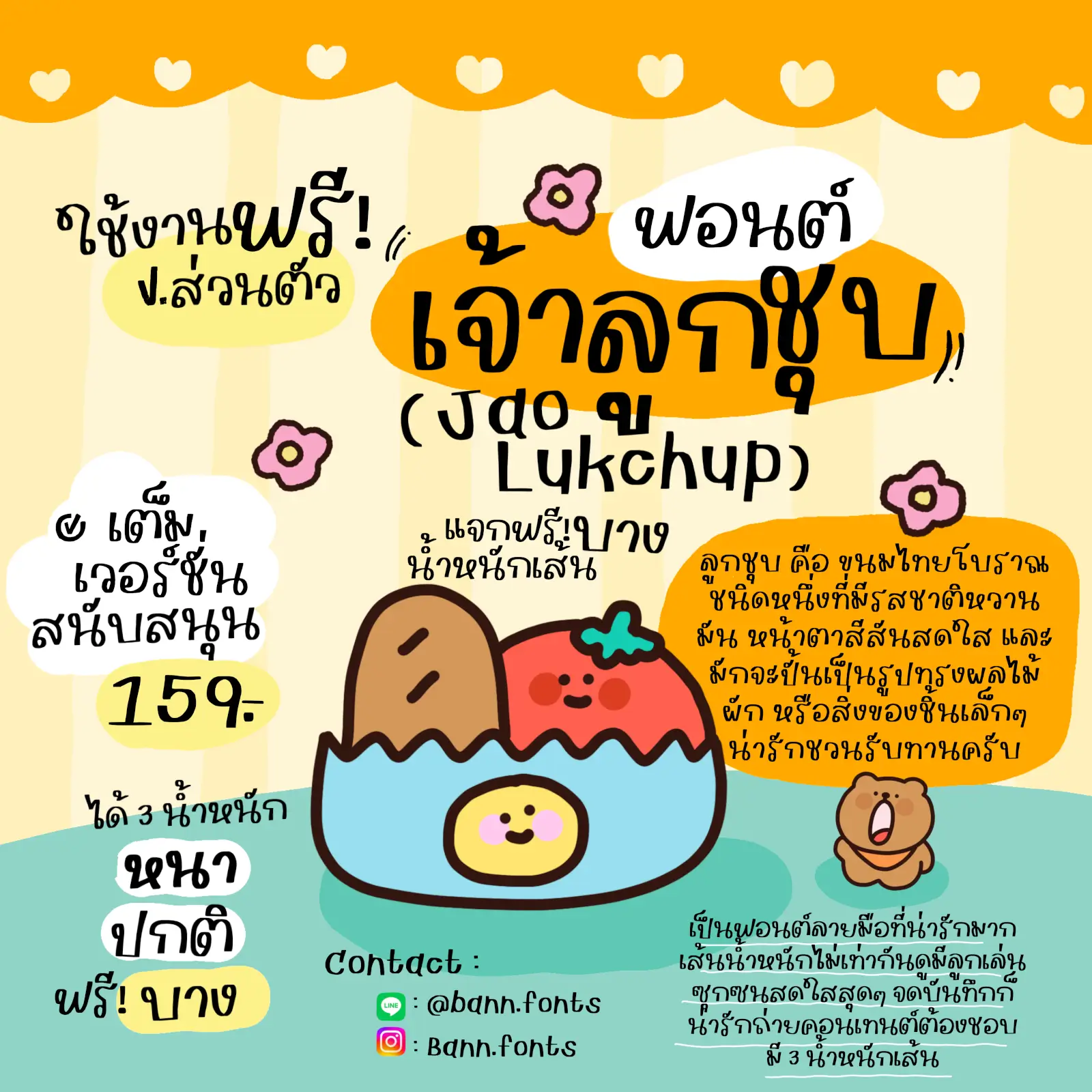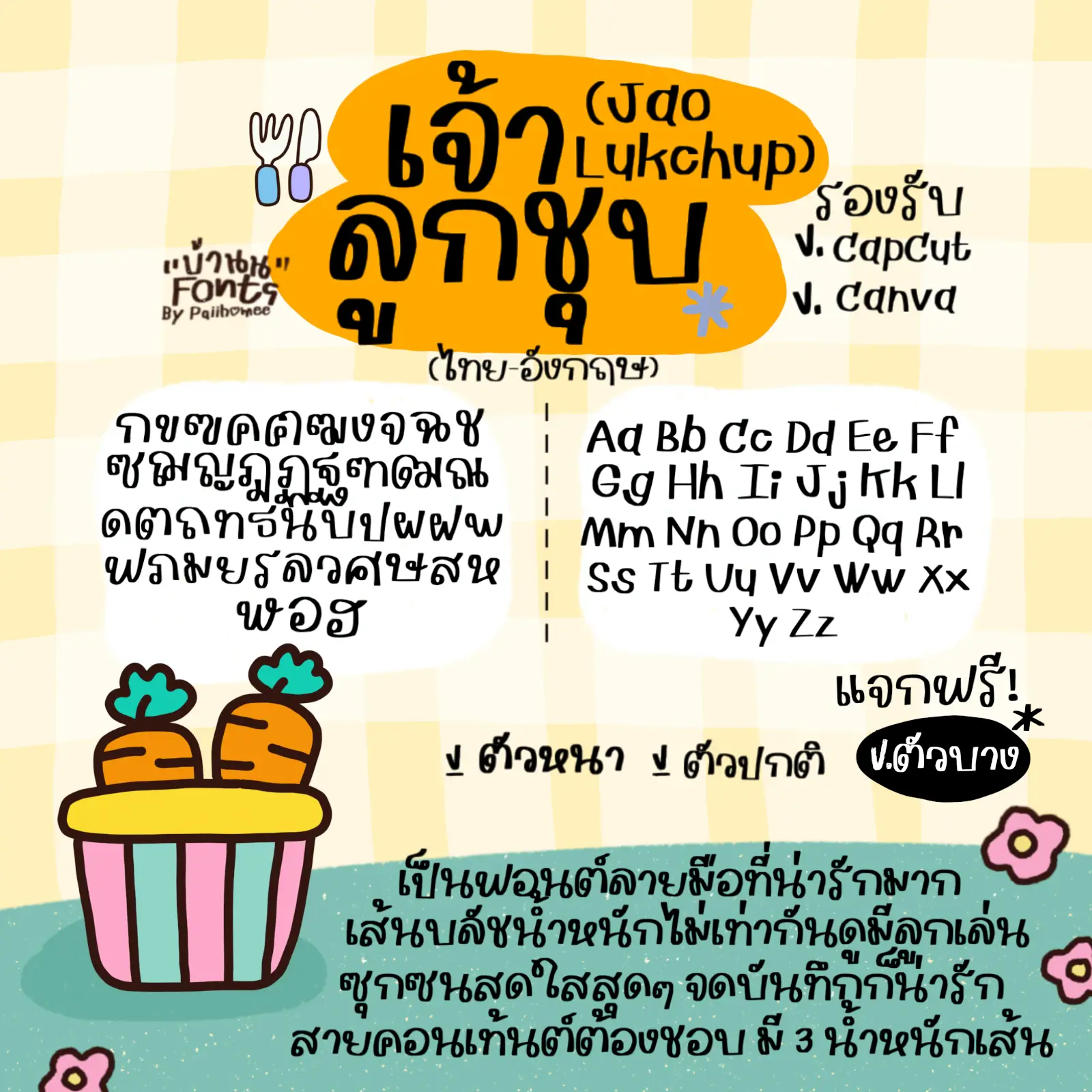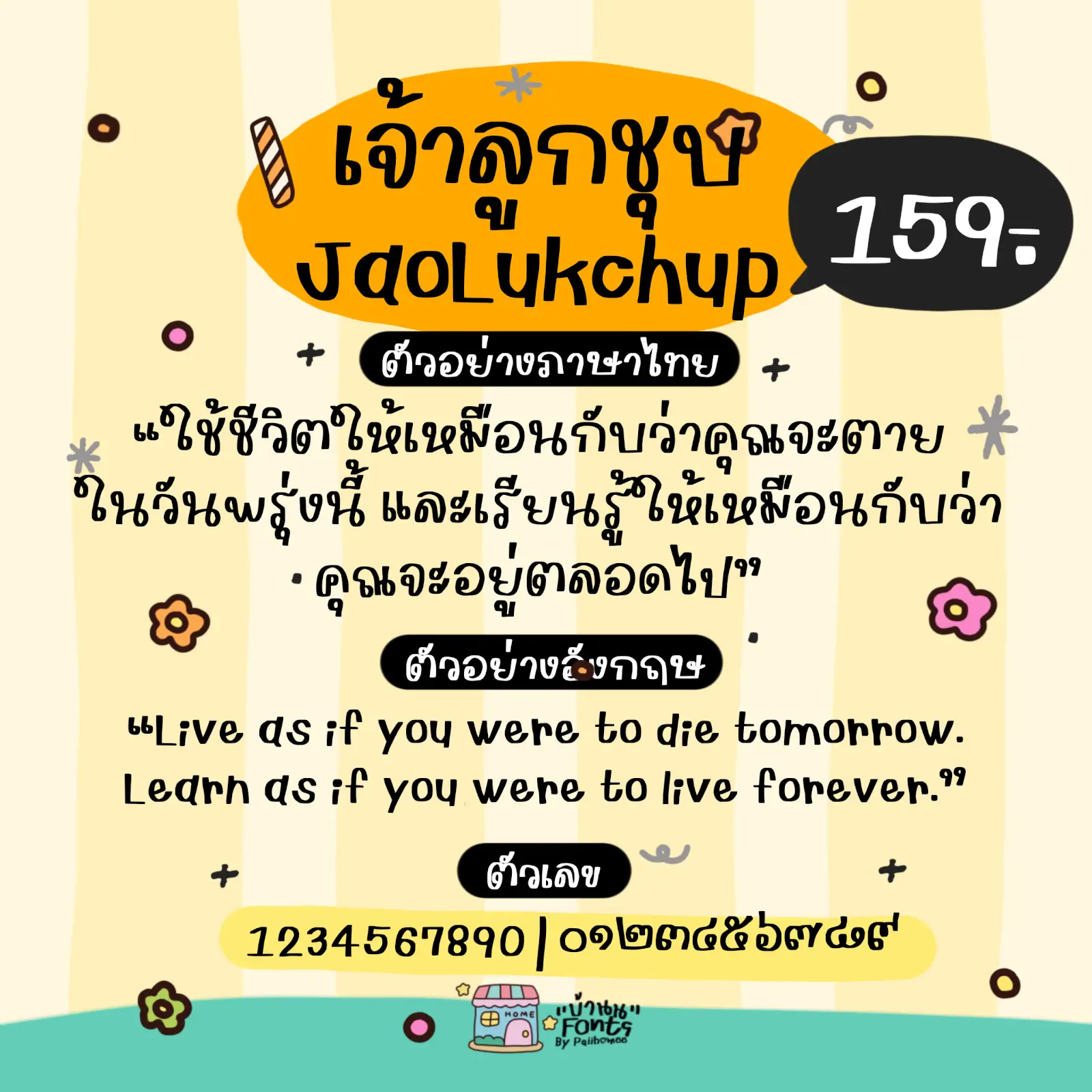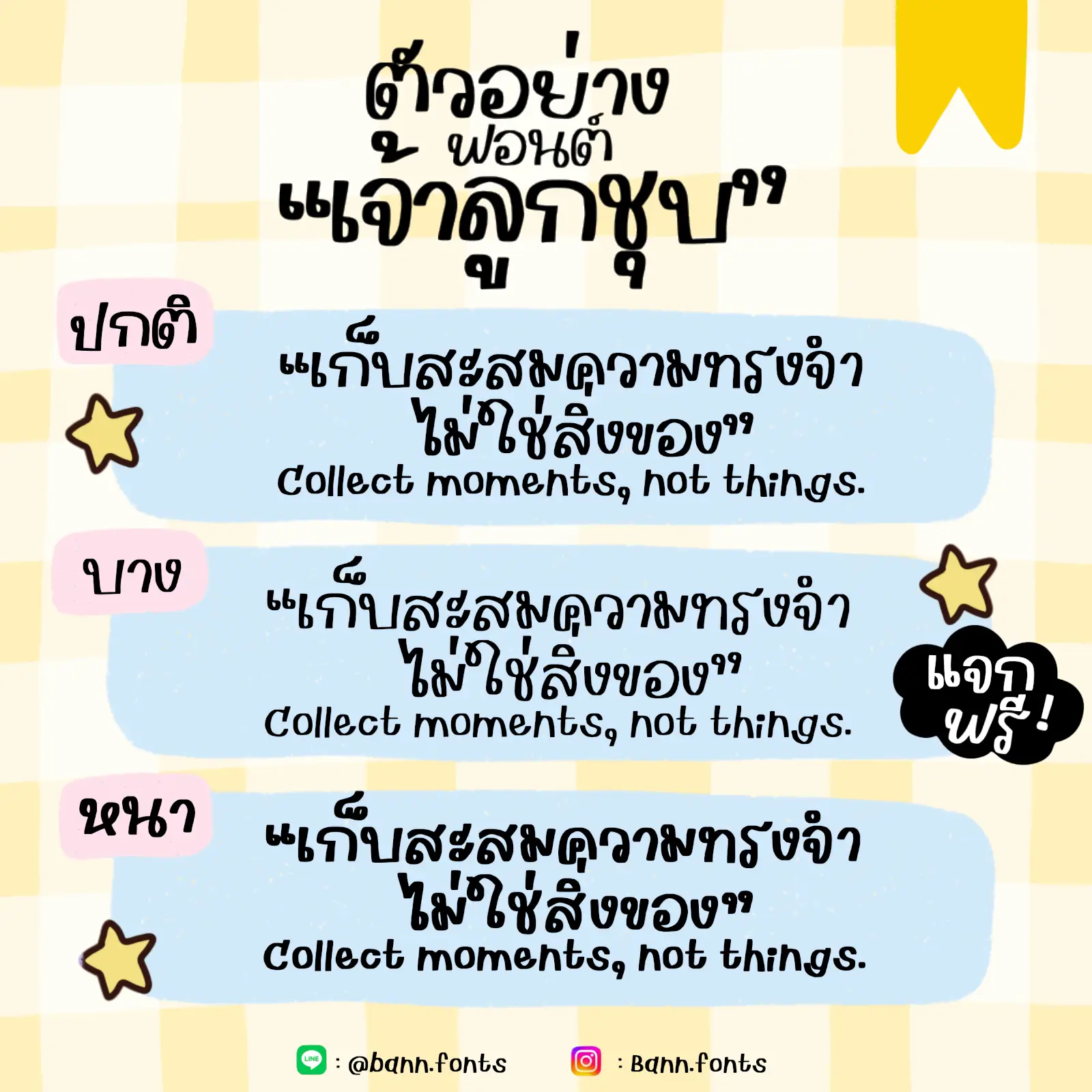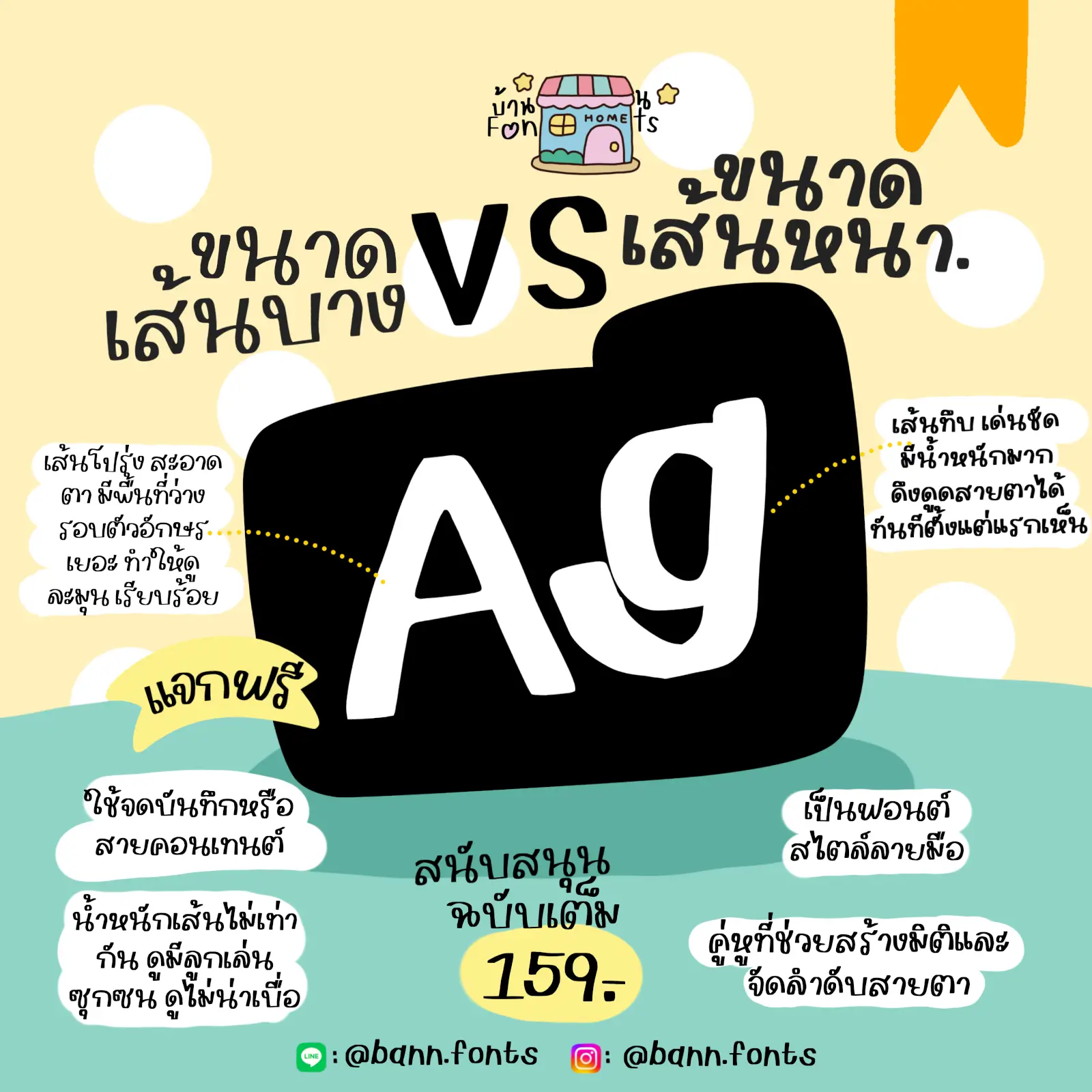
ฟอนต์เจ้าลูกชุบ – แจก เส้นบาง! ใช้งานแบบส่วนตัวได้ฟรี
แจกให้ใช้งานฟรี! สำหรับคนที่ชอบฟอนต์ลายมือ น่ารักๆ เรียบร้อยแต่ซุกซน
เพิ่มความน่ารัก x10! ต่อยอดทำปกคลิป แต่งสตอรี่ หรือใส่รีวิวสินค้าคือจึ้งงง
แนะนำว่า นำไปใช้งานกับการจดเนื้อหา สรุปงาน จดโน้ต จดบันทึก
หรือจะนำไปทำคลิป แต่งรูป ก็เริ่ดสุดๆ แนะนำเลย
แจกฟรี 1 สไตล์ (เส้นบาง)
เจ้าลูกชุบ (JaoLukchup)